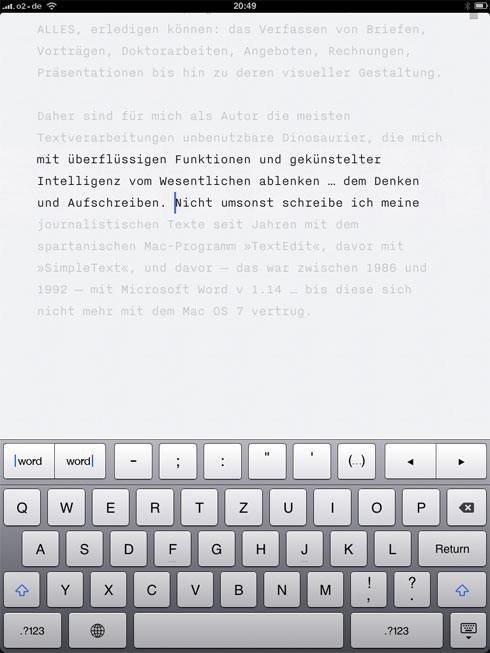
Ich schreibe diesen Text mit einer neuen Software, einer App, auf dem iPad. Sie heißt schlicht »Writer« und stammt aus dem Labor der Information Architects (iA). Writer hat ein schlichtes Ziel, nämlich das (kreative) Schreiben so einfach wie möglich zu machen. Andere Textprogramme wollen mehr, meistens ALLES, erledigen können: das Verfassen von Briefen, Vorträgen, Drehbüchern, Doktorarbeiten, Angeboten, Rechnungen, Präsentationen bis hin zu deren visueller Aufbereitung.
Daher sind für mich als Autor die meisten Textverarbeitungen unbenutzbare Dinosaurier, die mit überflüssigen Funktionen und gekünstelter Intelligenz vom Wesentlichen ablenken … dem Denken und Aufschreiben. Nicht umsonst verfasse ich meine journalistischen Texte seit Jahren mit dem spartanischen Mac-Programm »TextEdit«, davor mit »SimpleText«, und davor — das war zwischen 1986 und 1992 — mit Microsoft Word v 1.14 … bis dieses sich nicht mehr mit dem Mac OS 7 vertrug.
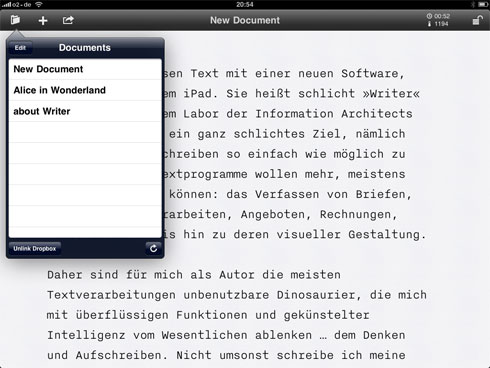
Weil ich aus Kollegengesprächen weiß, dass ich mit meinem Bedürfnis nicht alleine bin, frage ich mich oft, warum keines der großen Softwarehäuser, aber auch kein kleines, in der Lage ist, einen simplen Texteditor auf den Markt zu werfen. Vielleicht kann man damit nicht reich werden, was mich wundert, denn es gibt jede Menge nützlicher und preiswerter Utilities. Wahrscheinlich ist die marktbeherrschende Rolle Microsofts eine der Ursachen … und die Mutlosigkeit ihrer Nachahmer und Mitläufer (z. B. Open Office).
Nun gibt es seit einigen Monaten das iPad, das auf der fruchtbaren App-Infrastruktur des iPhones aufsetzt, wo Programme nicht viel kosten, aber Erstaunliches leisten. Und so dauerte es nicht lange, bis die erste Ankündigung einer simplen Schreib-App an mein Ohr drang, das war im Mai diesen Jahres auf der TYPO Berlin Designkonferenz. Oliver Reichenstein, Gründer und Geschäftsführer des schweizerisch-japanischen Designbüros Information Architects zeigte die ersten Screenshots seiner »Writing Machine«. Was er dazu erzählte, sorgte nicht nur bei mir für Begeisterung, sondern für Applaus im ganzen Saal.
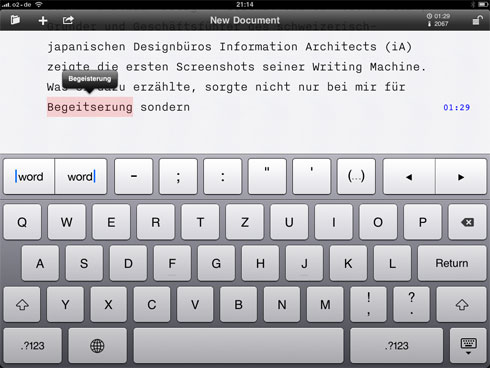
- Focus-Modus: 3 Zeilen scharf, der Rest grau
- Eigene Tastaturzeile für wichtige Schreibfunktionen
- Ablage/Speichern in die Wolke (Dropbox)
- angenehme, dezente Sounds
- eine der schönsten Korrespondenzschriften, Nitti Light von Bold Monday
- Zähler für Anschläge und Lesedauer
Dieser Text: 2683 Anschläge, 01:56 min Lesezeit.
Focus-Modus? So schwer wird es doch nicht sein, im eigenen geschrieben Text nicht hin- und herzuspringen, oder? Und warum sind dezente Sounds beim Schreiben besser als gar keine?
@ganzunten: Zu Hause mit der Bluetooth-Tastatur, unterwegs am Touch-Screen, warum ich mich dabei bücken soll, ist mir nicht so klar … Liegend hab ich noch nicht ausprobiert.
@Salim Maren: Less is more
Tolle Idee. Den Screenshots nach zu Urteilen auch eine sehr überzeugende Umsetzung, aber:
· Auf dem iPad kann ich persönlich nicht gut schreiben. Und ohne Autokorrektur sähe das bei mir wirklich wild aus. Zumindest würde ich sie mir als Option wünschen.
· Es ist eine iPad-App. Wie viele ernsthaft schreibende Menschen haben ein iPad und arbeiten damit? Das ist doch wirklich albern so eine Idee am iPad umzusetzen. Und selbst wenn es von den Verkaufszahlen und der Resonanz her ein Erfolg werden sollte, finde ich es schlichtweg doof — und auch etwas elitär — so ein Programm vorerst ausschließlich für das iPad herauszubringen.
· der Einwand von ganzunten
Ich schon. Normalerweise arbeite ich am Desktoprechner, deshalb lohnt sich für mich kein aufgebrezeltes Laptop. Wenn ich doch mal unterwegs bin, ist das ipad sehr nützlich und mit der Anstecktastatur sogar brauchbar.
Was Schreibprogramme angeht, geht es mir wie Jürgen: SimpleText, Textedit etc. – weil das ganze Gedöns von Word oder Indesign nur dazu führt, dass man anfängt seinen Text hübsch zu formatieren und so den Schreibprozess unterbricht.
Was das Schreiben unterwegs betrifft, so stellt dies für mich kein Problem dar, da wir aus genau diesem Grunde eine eigene Tasche in die Realität gebracht haben.